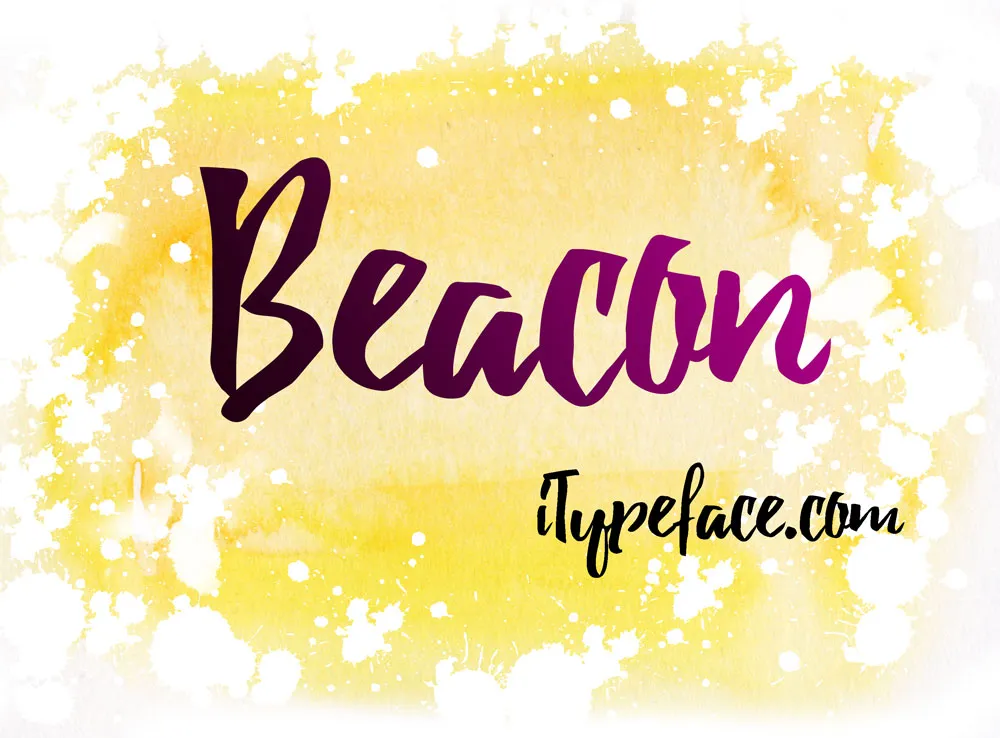
A Beacon Font é uma atraente escolha para qualquer designer que busca dar vida a seus designs com um toque especial. Embora seja classificada como tipo brush, Beacon oferece precisão e elegância ao mesmo tempo. Desenvolvida com mão d’água por um profissional da TypeFace, ela traz uma personalidade única e sofisticada para qualquer projeto. Reconhecível pela sua natureza original e não replicável, a Beacon é perfeita tanto para aplicações pessoais quanto comerciais. Ela oferece um toque único que tornará seus projetos ainda mais interessantes e chamativos. Se você busca uma fonte de qualidade que possa realçar seu trabalho em diferentes tipos de conteúdo, Beacon Font é definitivamente algo a considerar.